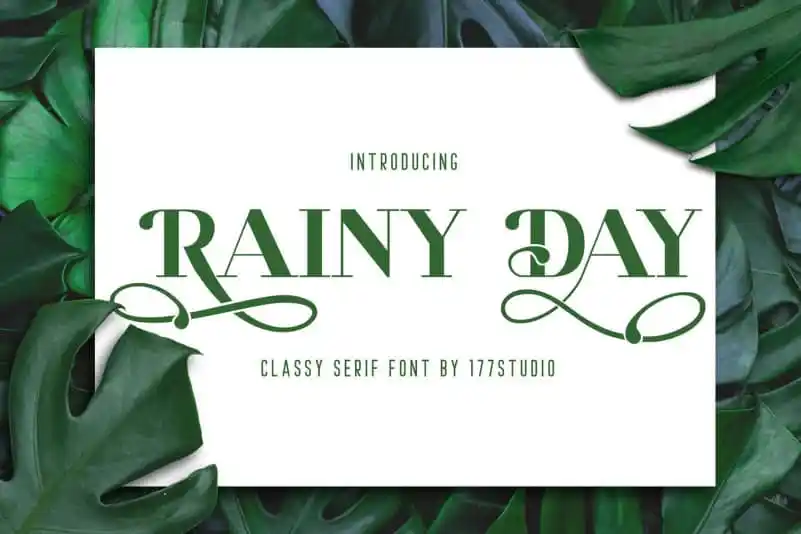
RAINY DAY Serif Font – Download Grátis
A Fonte RAINY DAY Serif é uma elegante e mágica serif que oferece uma sensação única para qualquer projeto. Com seu design minimalista e sofisticado, esta fonte pode ser facilmente combinada com um vasto conjunto de ideias criativas, permitindo destacar o seu trabalho e fazer dele algo único. A RAINY DAY Serif é perfeita para criações que exigem uma aparição imponente e distintiva, tornando-a a escolha ideal para quem busca personalidade em cada projeto. Seja no design de sites profissionais ou na edição de publicações digitais, essa fonte adicionará um toque especial à sua visão, dando vida e profundidade ao que você cria.